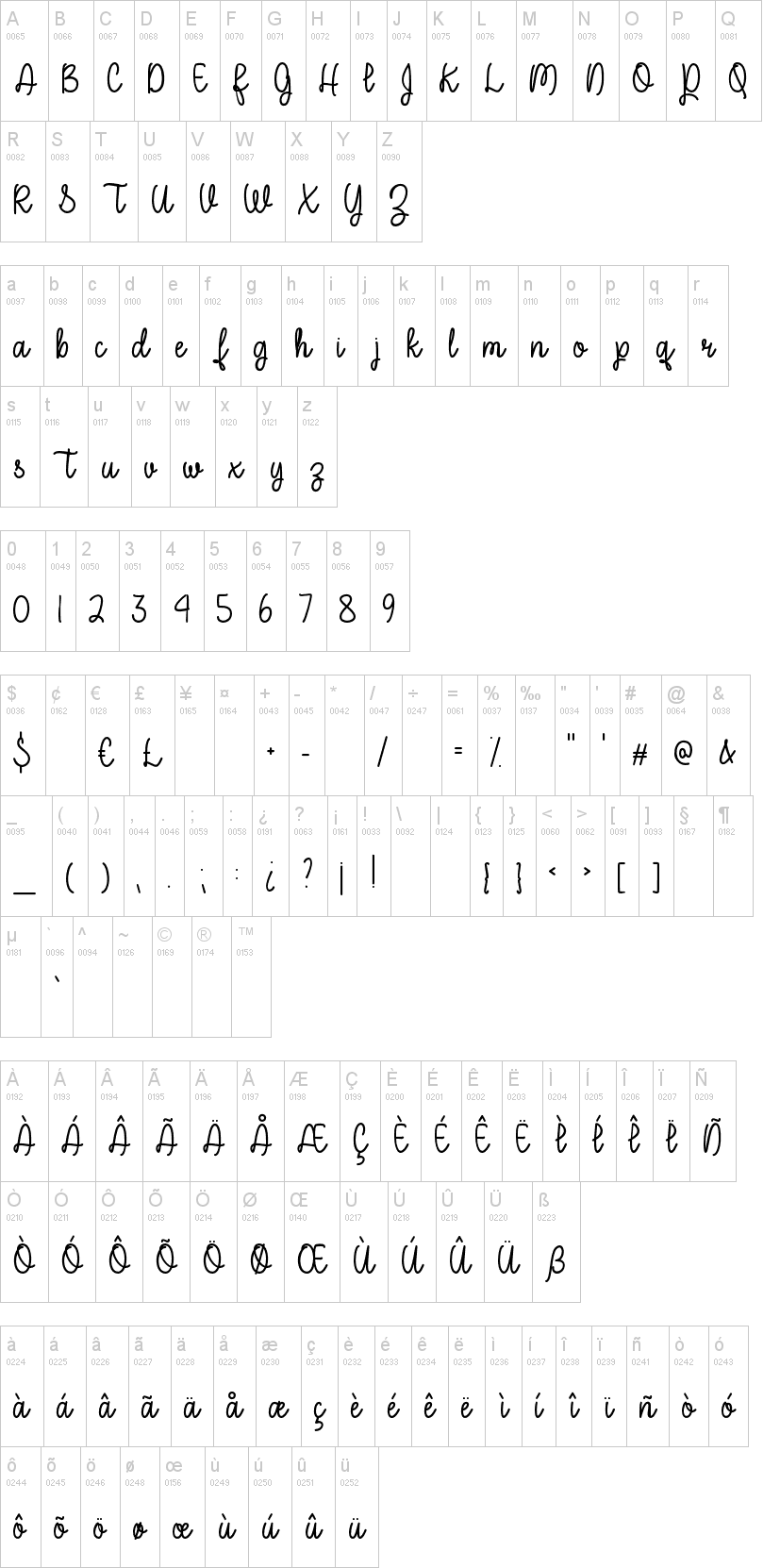
A Perfect Place 字体是一款经典、简洁的英文字体,它以清新、简约的设计风格受到广大用户的青睐。A Perfect Place 字体具有高度的可读性,适用于文档、广告、报纸等各种印刷品的排版。它的字形特点清晰、细腻,字体的细节也非常精致,使用时能够给用户带来良好的体验。内容介绍
A Perfect Place是一款非常不错的手写艺术字体,具有很好的视觉感,适合于文化类的宣传设计、商业类品牌的广告和产品包装设计以及个性化文字排版等较多场景。